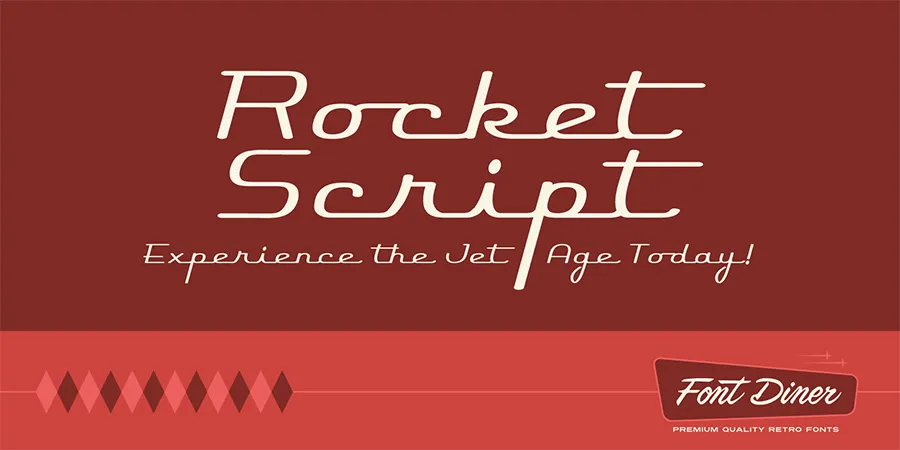
A fonte ‘Rocket Script’ é uma opção gratuita para designers que querem dar um toque nostálgico a seus projetos. Desenvolvida pelo designer Hamilton, esta font retro oferece uma maneira fácil de incorporar um ar vintage em qualquer projeto visual. Ideal tanto para logotipos quanto para posteres e camisetas, ‘Rocket Script’ é perfeitamente adaptável às muitas necessidades do design gráfico contemporâneo. Seja você um designer que busca tornar suas criações mais nostálgicas ou aqueles que simplesmente adoram a década de 70, esta fonte não pode faltar no seu arsenal de recursos. Com sua elegância e originalidade, ‘Rocket Script’ é uma excelente opção para quem procura inspiração nos anos 1950 e 60. Aproveite suas oportunidades criativas com essa fonte única que vai lhe dar um visual retro imediatamente.